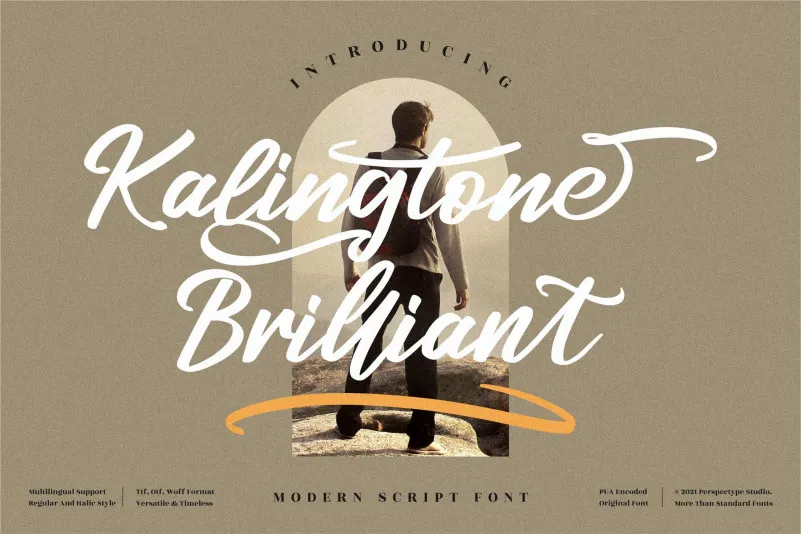
A fonte ‘Kalingtone Brilliant’ é uma opção incrivelmente atraente para designers que procuram dar destaque às suas identidades visuais com estilo elegante e fresco. Ela tem um aspecto cíntaro, ou seja, escrita cursiva, mas ao mesmo tempo suave o suficiente para manter-se acolhedora. Ideal para headlines e logotipos que precisam de uma pitada de personalidade nostálgica, a fonte ‘Kalingtone Brilliant’ tem uma característica marcante: ela é poderosa, confiante e dinâmica. Esta fonte pode fazer um enorme diferencial em qualquer projeto gráfico, adicionando ao seu design algo especial que vai cativar os olhos do espectador imediatamente. Como designer, não há melhor maneira de tornar sua marca mais memorável do que a incorporação da ‘Kalingtone Brilliant Font’.